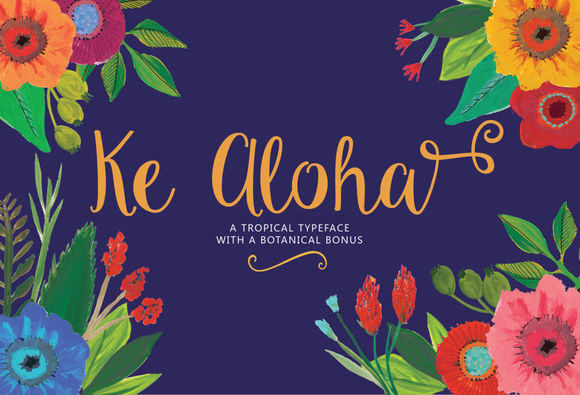
A Ke Aloha Font é uma excelente adição para qualquer designer que busca personalidade e estilo único em suas criações digitais. Seu design original e autêntico, inspirado na arte de desenhar a mão, oferece um conjunto impressionante de elementos florais e ornamentados que podem ser facilmente reformatados e manipulados com precisão. Com mais de 50 elementos distintos e artesanal, você pode personalizar cada detalhe da maneira que desejar — desde pequenos adereços até grandes obras de arte. Essa fonte é especialmente atraente para designers gráficos que querem incorporar um toque de elegância na sua produção. Cada elemento pode ser redimensionado e editado com extrema facilidade, sem necessidade de software especializado — isso torna o processo de criação ainda mais rápido e fácil. Além disso, a fonte oferece uma transparência automática nos fundos, permitindo que você personalize as cores do preenchimento e da linha, adicione sombras para dar realidade e dimensionamento aos seus desenhos florais. Essa font é perfeita tanto para uso em software de design como Illustrator ou Photoshop, quanto para criação rápida no Word. Você pode usar sua biblioteca de ferramentas favoritas desses programas para adicionar textura ou fazer um desenho ainda mais sofisticado, tudo a partir das plantas e flores que criou. Com a Ke Aloha Font, você terá inúmeras oportunidades de criar trabalhos incríveis. Use suas habilidades com stencil, impressão em estampar, arte para paredes grandes ou pequenas, desde as mais simples até os designativos, como logotipos e embalagens de presente. Sem dúvida, essa font é um dos recursos mais valiosos do seu arsenal de ferramentas.